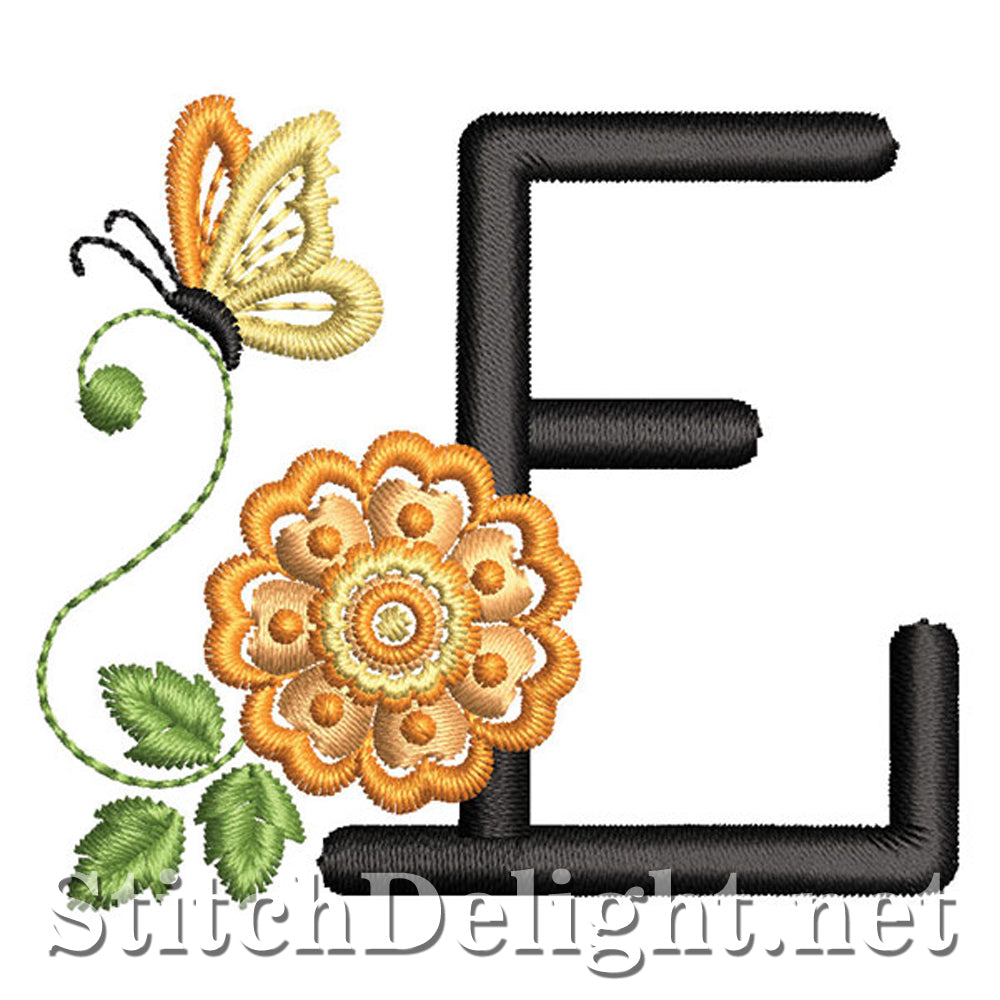
SDS1236 Sunset Bloom-lettertype E
Personaliseer uw project met deze stijlvolle monogramset met prachtige zonsondergangbloesems en vlinders - BX-versie voor Embrilliance-software alleen inbegrepen bij de aankoop van VOLLEDIGE lettertypen, niet voor losse letters - Letterhoogte is 2,1 inch / 55 mm